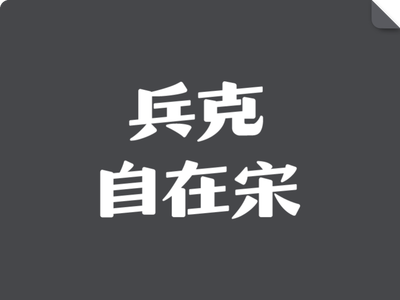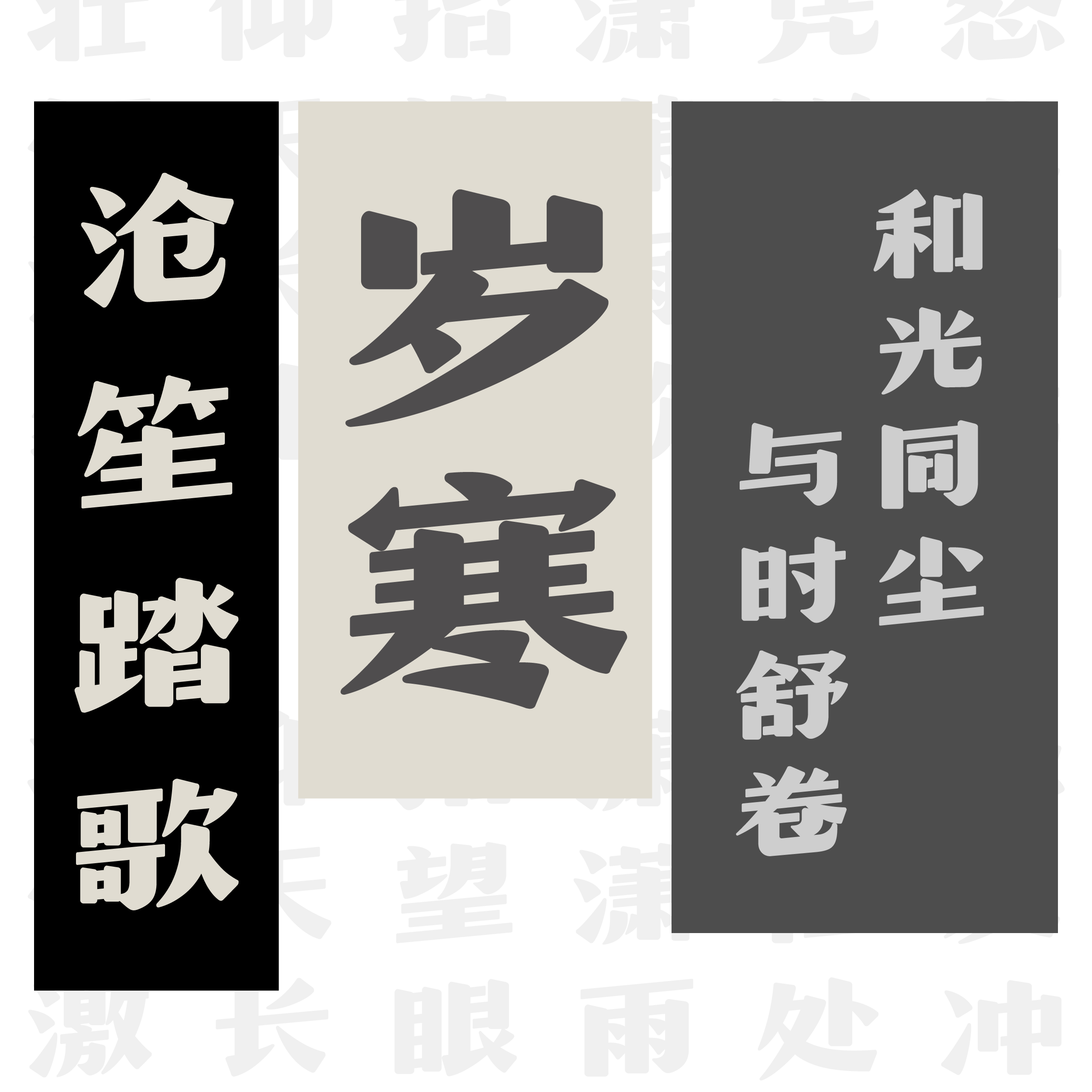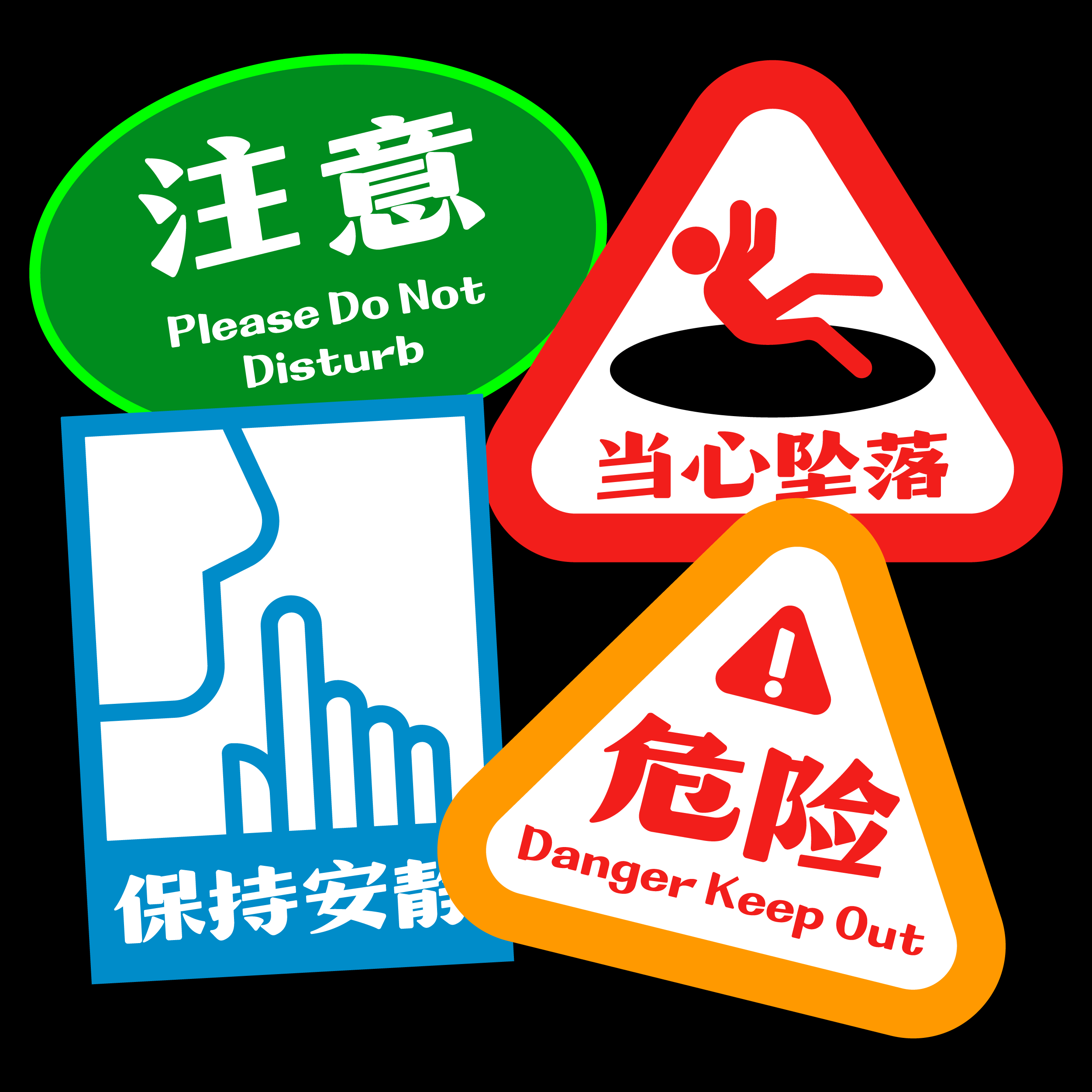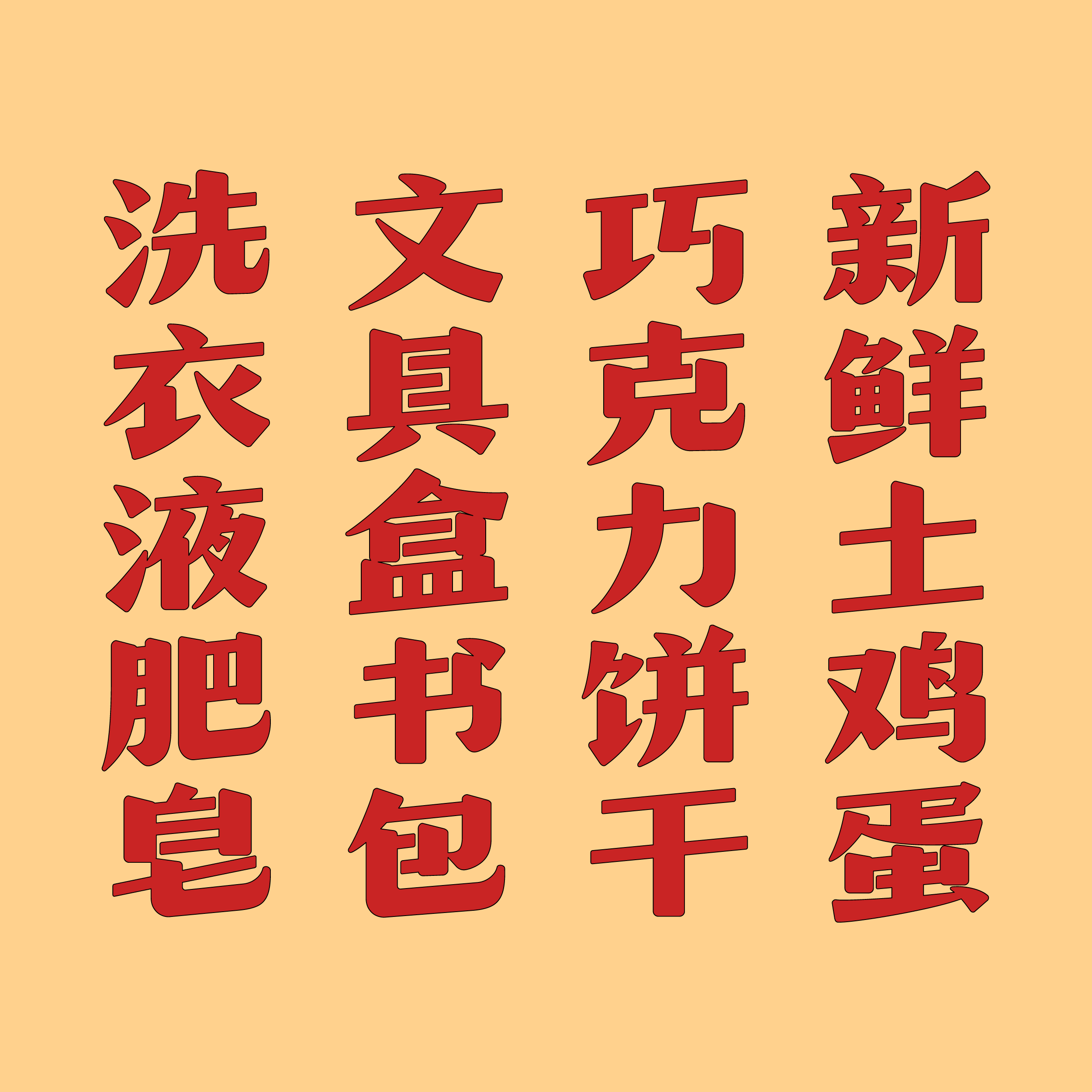
兵克自在宋
兵克自在宋,兵克自在宋,追求明快轻盈的视觉效果,笔画末端采用了圆角处理,这一细腻的设计不仅使字体整体更显柔婉与温润,更增添了一份和谐与亲近感,仿佛能触摸到文字背后的温度与情感。字形整体向右上方倾斜,不仅打破了传统字体的刻板印象,更在视觉上形成了一种动态的平衡,赋予文字以活泼的韵律感与跃动的生命力。兵克自在宋适用于多种设计场景,如标志设计、包装设计、广告设计、印刷品设计等设计领域。字 体 ID:1457